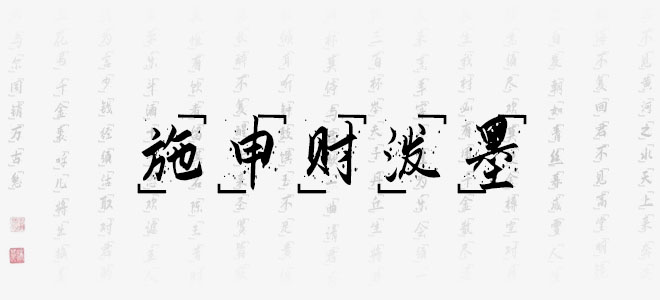
施申財(cái)潑墨是一款書(shū)寫(xiě)很新穎的字體,具有強(qiáng)烈的視覺(jué)沖擊力。適用于海報(bào)、電商海報(bào)設(shè)計(jì)、店鋪設(shè)計(jì)、標(biāo)志設(shè)計(jì)、字體設(shè)計(jì)等領(lǐng)域。
施申財(cái)潑墨